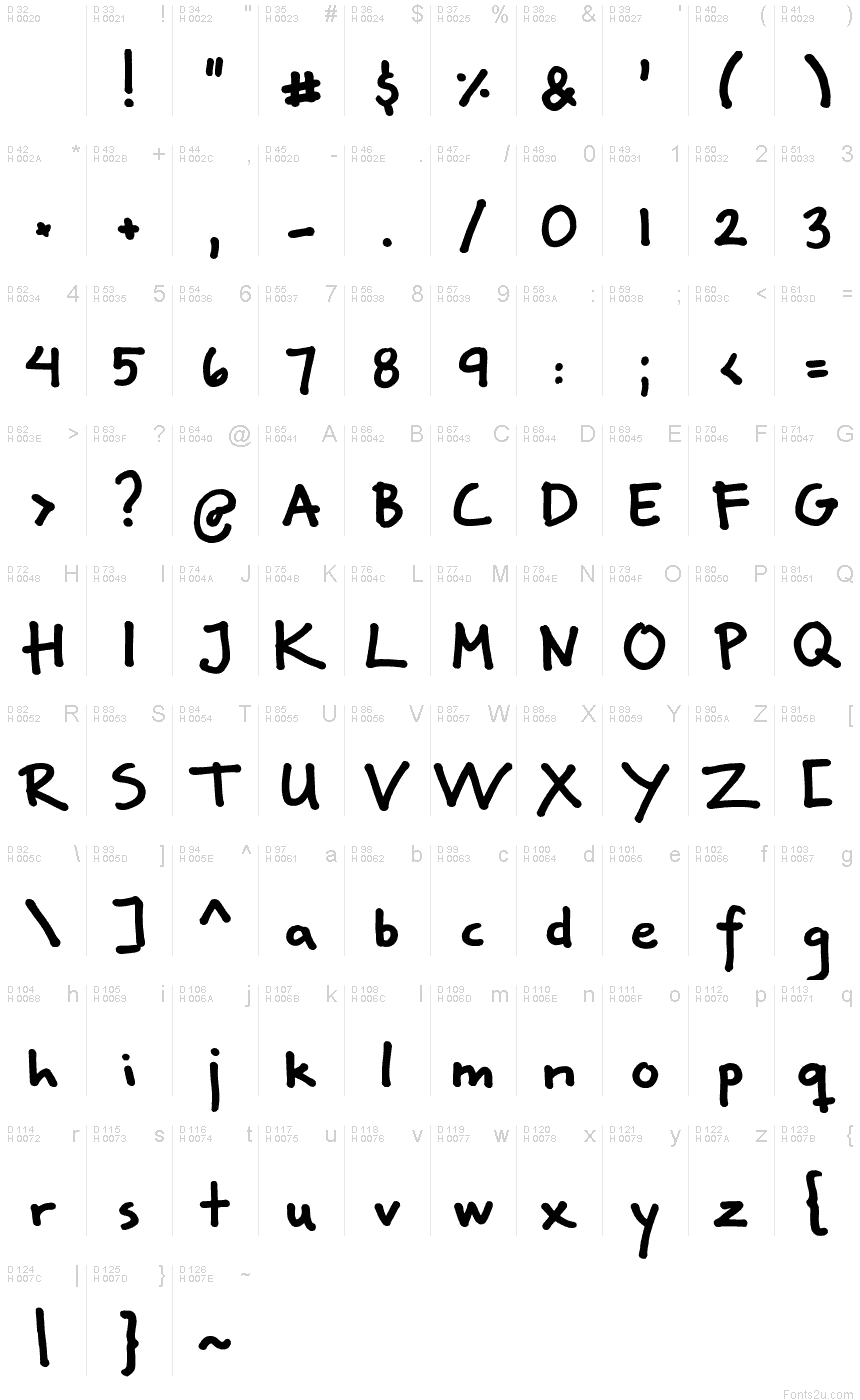
FG Klara od Font Garden je bezplatné ručně psané písmo, které zachycuje pocit silného fixu vedeného sebejistě po papíře – je živé, trochu rozverné, ale stále dobře čitelné. Zaoblené tahy a uvolněný, hravý rytmus mu dodávají přátelský, lidský nádech, který však nesklouzává k chaosu, takže v jednom řádku získáte osobitost i přehlednost.
FG Klara je bezplatný font, který vynikne na obálkách dětských knížek, školních plakátech, narozeninových pozvánkách, citátech na sociální sítě, hravých logách a nálepkách, kde chcete vyvolat pocit tepla a spontánnosti. Jeho výrazné, inkoustové tvary dobře fungují ve větších velikostech a zůstávají čitelné i v krátkých odstavcích. Zkombinujte ho s jednoduchým bezpatkovým písmem pro hlavní text a FG Klara nechte vyniknout v nadpisech, štítcích a rukopisných akcentech.